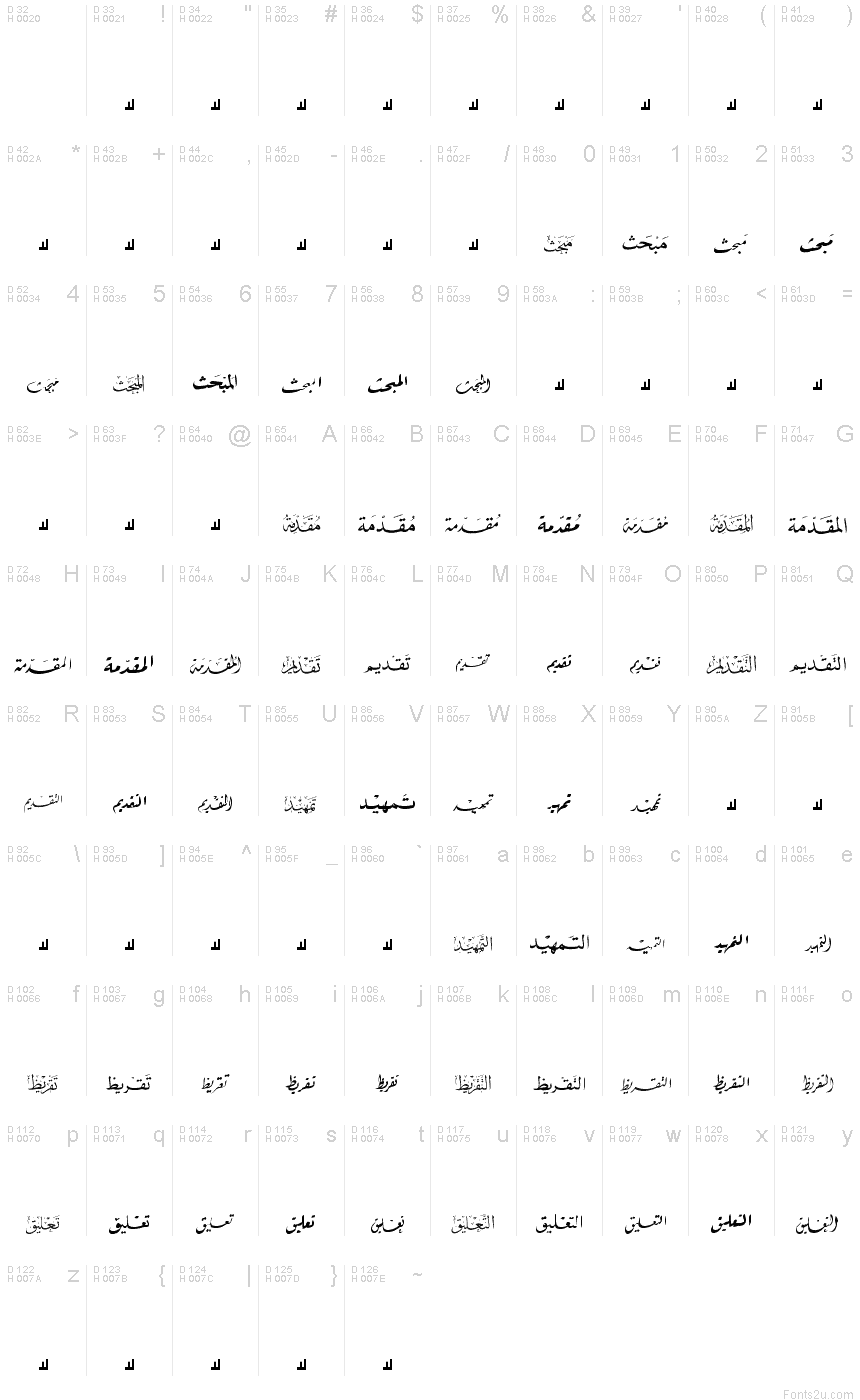
Mcs Book Title 2 هو خط عربي مجاني للعناوين، يتميز بطابع أدبي وكاليغرافي. تمتد الحروف في ضربات طويلة وانسيابية مع زوايا حادة ومحددة، مما يمنح الخط إيقاعاً متزناً يبدو مصمماً خصيصاً لأغلفة الكتب والعناوين الرسمية، بدلاً من النصوص الطويلة.
يتناسب الخط مع أغلفة الكتب، وعناوين المجلات، والملصقات الثقافية، وتصاميم المعارض، والبطاقات التعريفية حيث تحتاج بضع كلمات إلى الحضور والإيقاع العربي المميز. وباعتباره خطاً مجانياً، فهو مثالي أيضاً لافتتاحيات الفصول وعناوين الأغلفة القصيرة، لأن امتداداته الأفقية الواسعة وتفاصيله الدقيقة تجذب الانتباه بفعالية في الاستخدامات المقتضبة والبارزة.